施申财漆书体以北魏楷书笔意书之,间夹隶书,字体方正,字态静穆古拙,看似字字断开,而其间笔意顾盼映带,整套字体给人以一种古朴生拙的气息。外形粗壮豪迈、外刚内柔,突出表现了中国书法线条美与力量美。
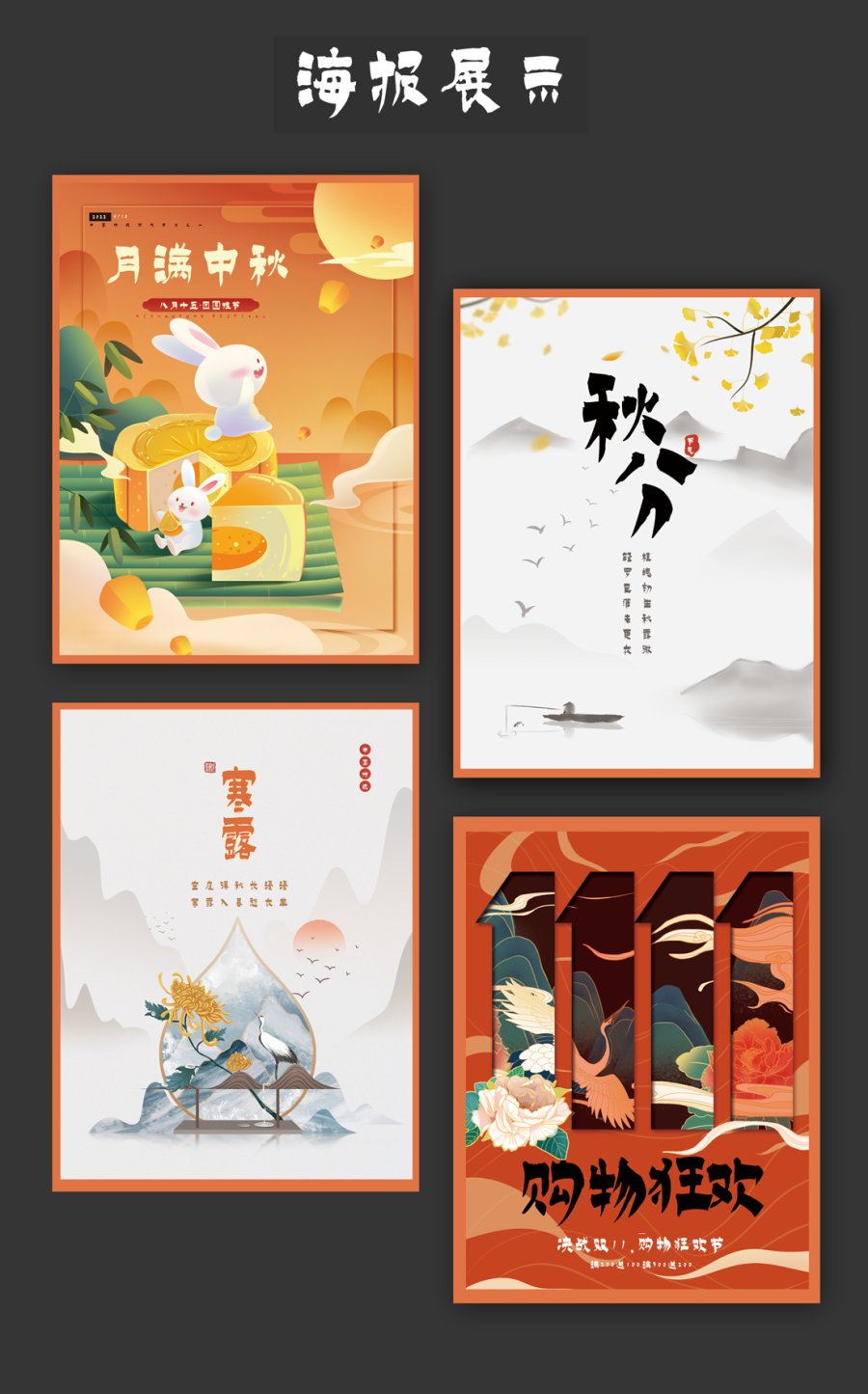
韩绍杰马服简体采用韩绍杰老师书写的毛笔字制作而成,该字体行笔轻盈运笔稳实,缓慢,便捷,线条追求流畅、明快, 属于书法大字榜书范畴。该字体笔画造型奇特,点画之间呼应紧密。点画活泼,点、钩、挑等动感笔画明显增多。行笔间有许多虚笔,蹲驻提衄,只在毫发之间,似有若无。